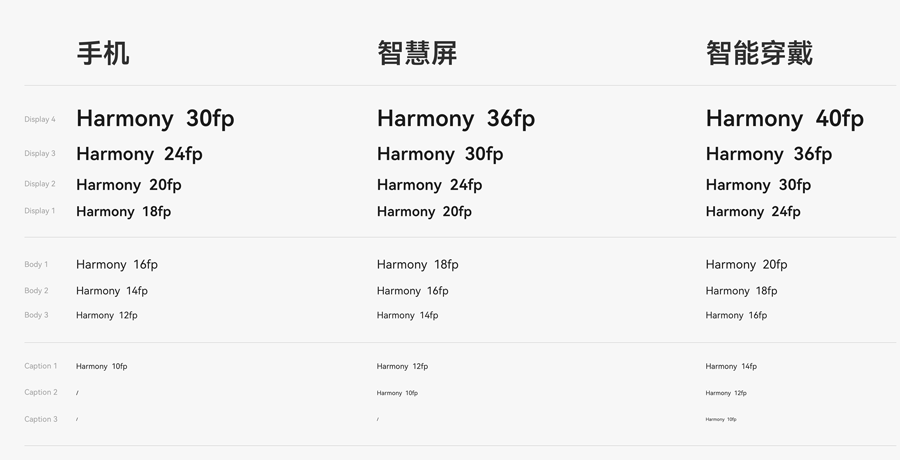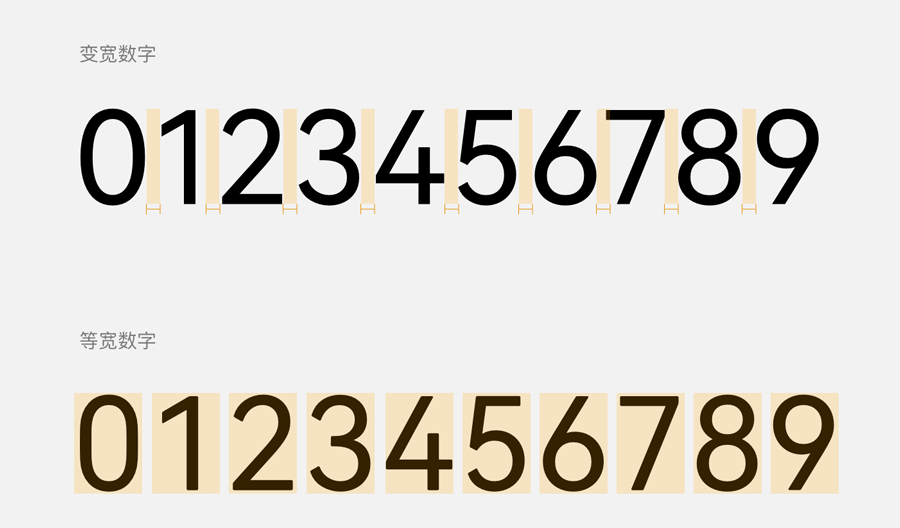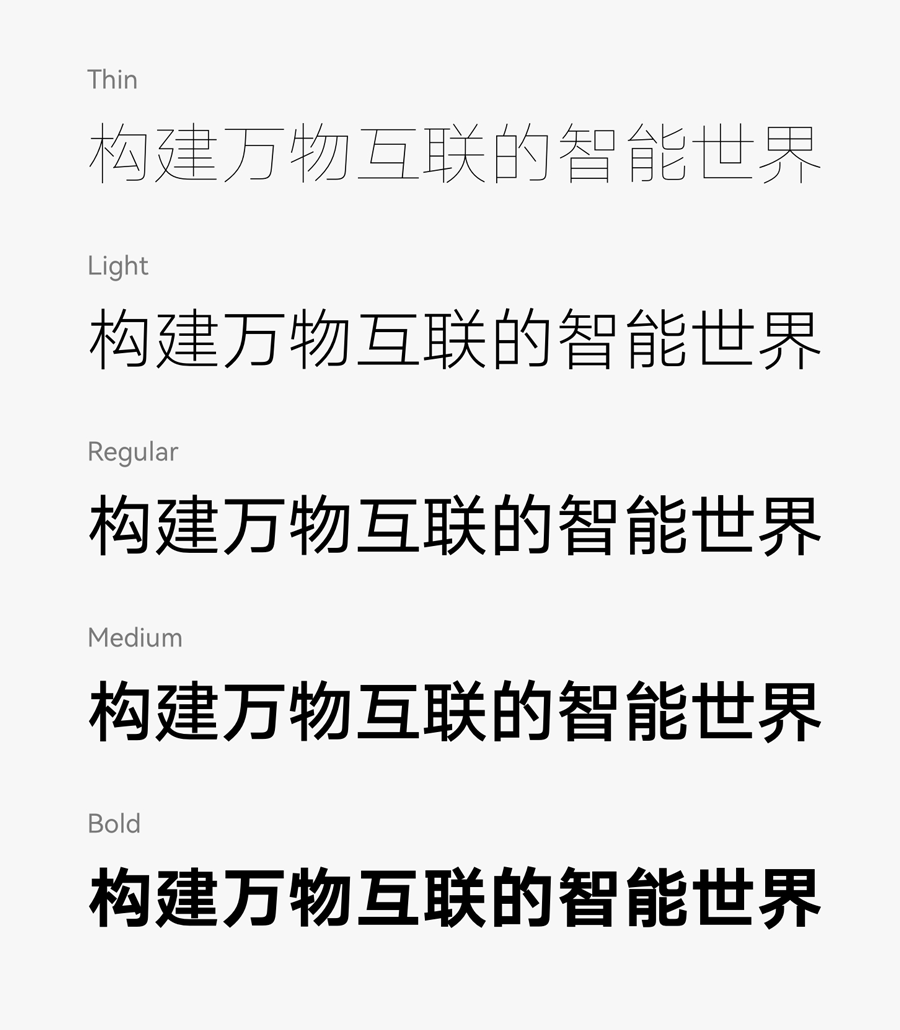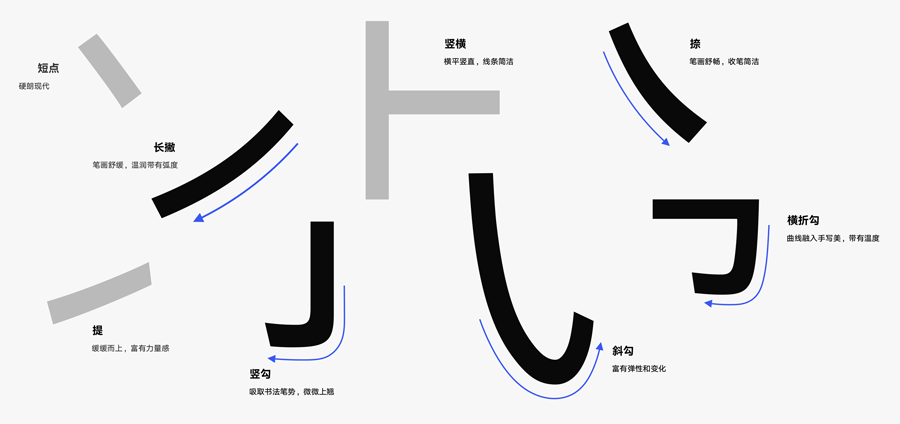
HarmonyOS Sans(鸿蒙字体) 是由华为与汉仪字库联合打造的一款无衬线字体,专为鸿蒙操作系统 (HarmonyOS) 而设计,于2021 年 6 月 8 日正式发布,并随鸿蒙系统开源而开放授权,个人与企业均可免费商用。
HarmonyOS Sans 支持简体中文、繁体中文、拉丁、西里尔、希腊、阿拉伯 5 大书写系统、覆盖 105 种语言。采用的是无级可变字体技术,提供Thin、Light、Regular、Medium、Bold、Black等多种字重,可以满足不同语言环境和使用场景。
HarmonyOS Sans 在设计上 80% 基于传统黑体,20% 又借鉴了楷体,采用 Sans-serif(无衬线)设计。字体简洁、清晰、易读,尤其是在 UI 界面上具有更良好的屏幕显示效果,目前已完美融入华为手机、平板、智能穿戴等设备中。